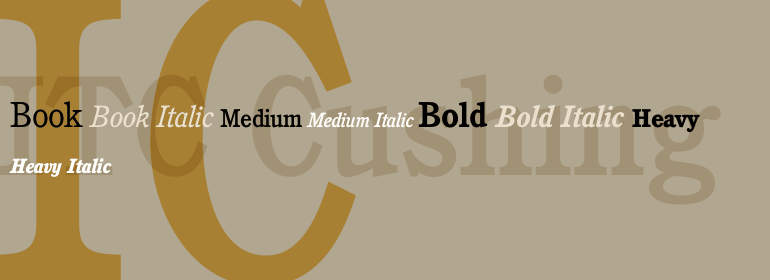
ITC Cushing™
ITC Cushing™,这款字体结构工整、笔画清晰,兼顾美观与易读性,适用于标题、正文、海报、包装、LOGO 等多种场景。字形优雅稳定,风格百搭耐看,适配日常排版与创意设计,让文字呈现更舒适、更具质感。ITC Cushing™一笔一画,皆是细节,以均衡的比例、流畅的线条打造舒适视觉体验,字形端正大气,风格简约现代。无论是商业设计、品牌宣传还是日常排版,都能轻松驾驭,让文字更有格调与力量。ITC Cushing™字体下载。
字体品牌: ITC(Monotype) 设计师:Pacella,Vincent 字体分类:衬线体 字体属性:外文 字符集:Unicode 发布时间: 2018